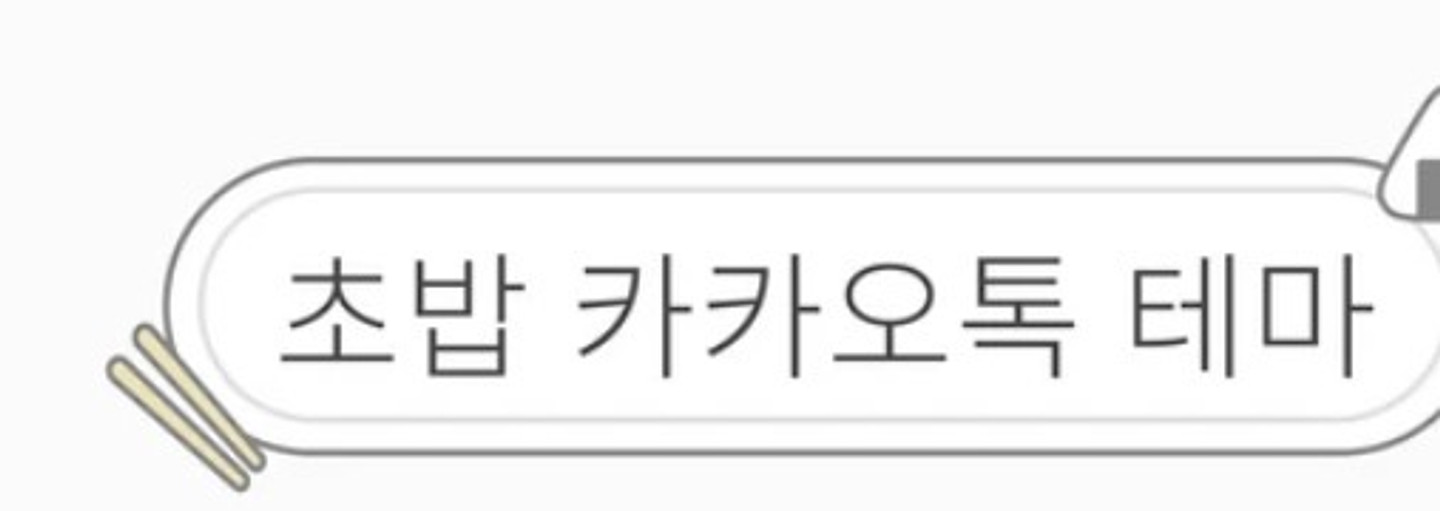
Sandoll 성경
Sandoll 성경(유료)폰트입니다! https://www.sandollcloud.com/font/83/Sandoll-Seongkyeong
만화~웹툰에서 주로 쓰이는 것 같아요. 당장 이 사진도 2차창작 만화에서 갖고 왔어요. 이 폰트를 엄청 뒤져봐도 똑같은게 안보이더라고요... 무슨 폰트인지 아시는 분이 계실까요?